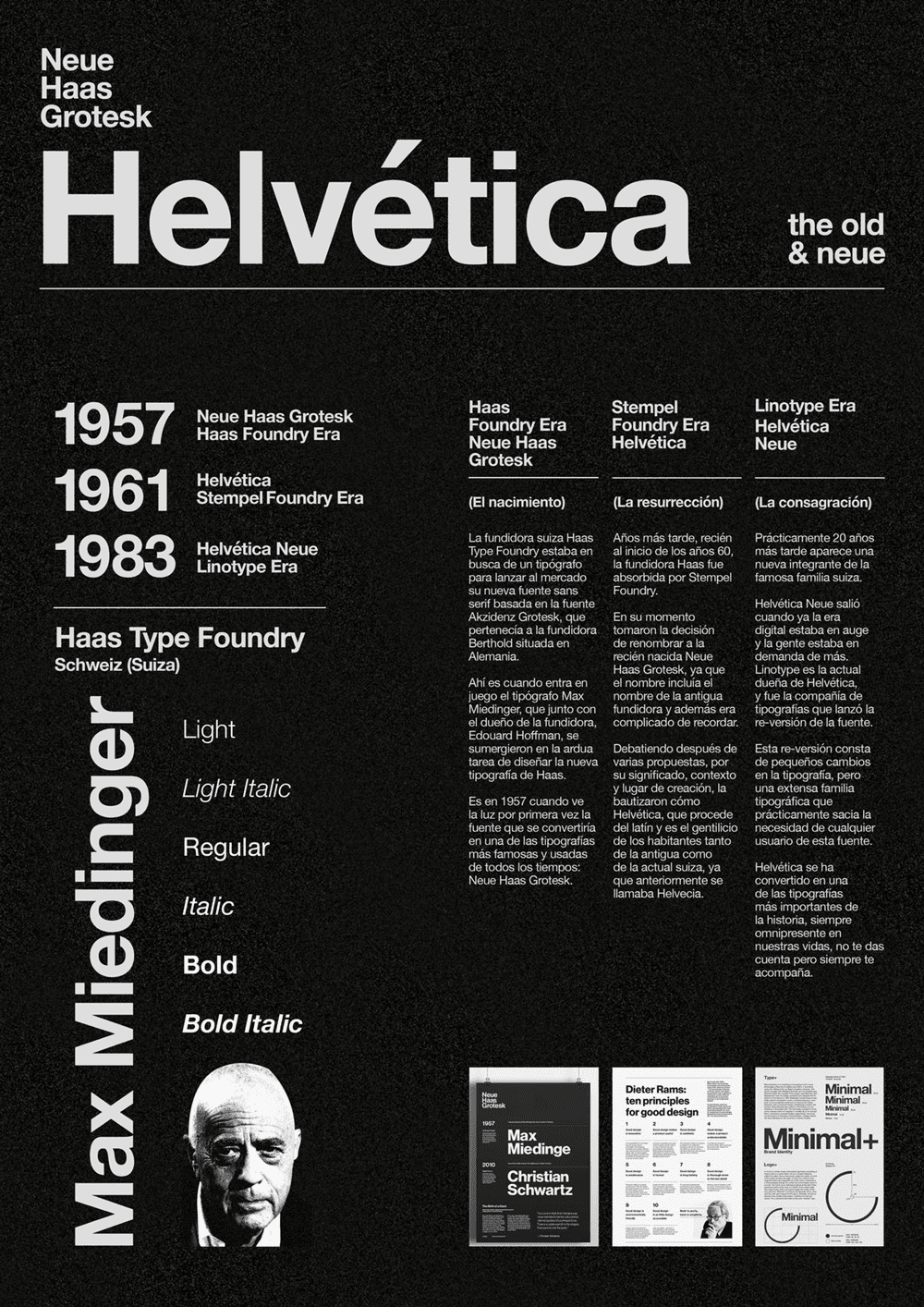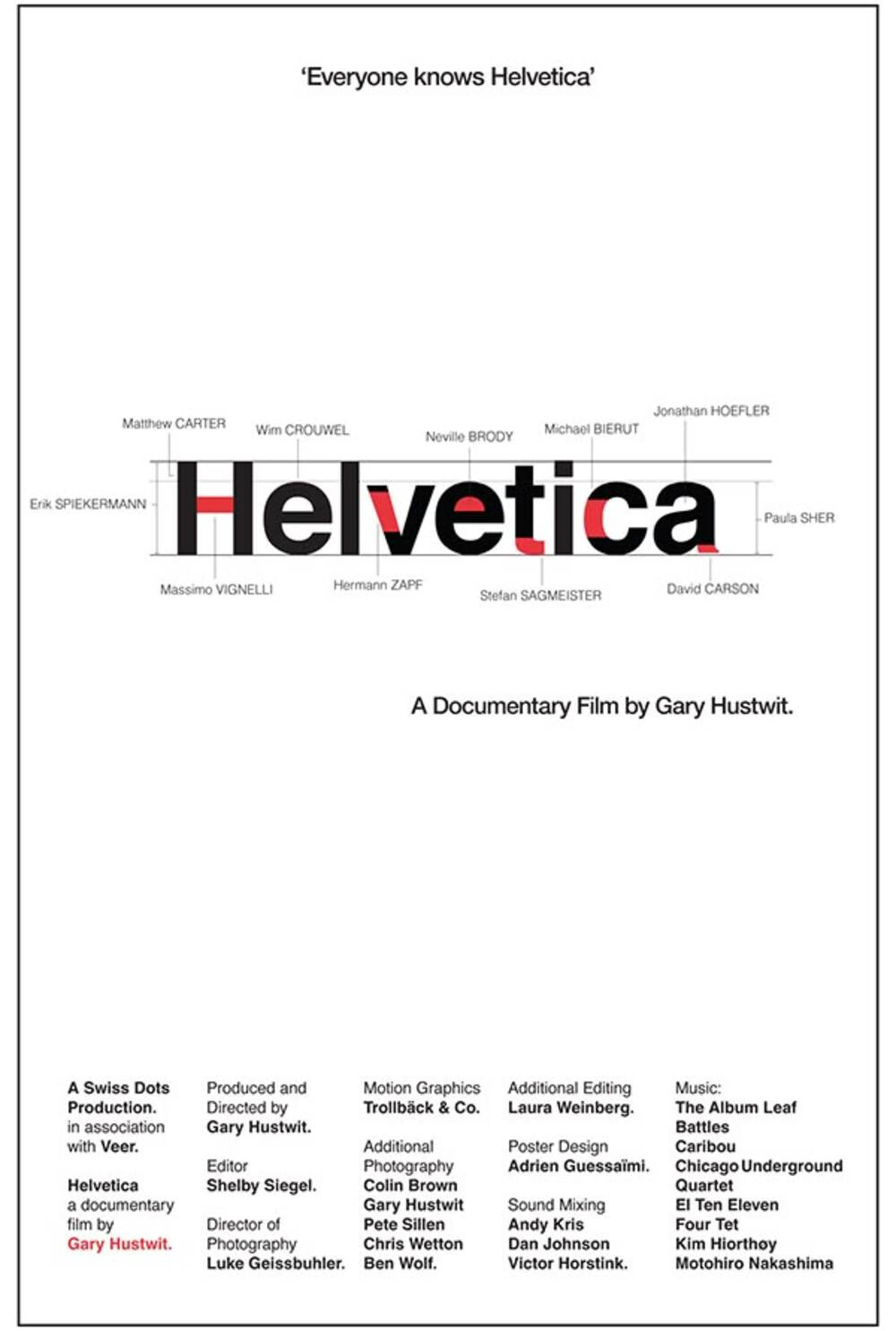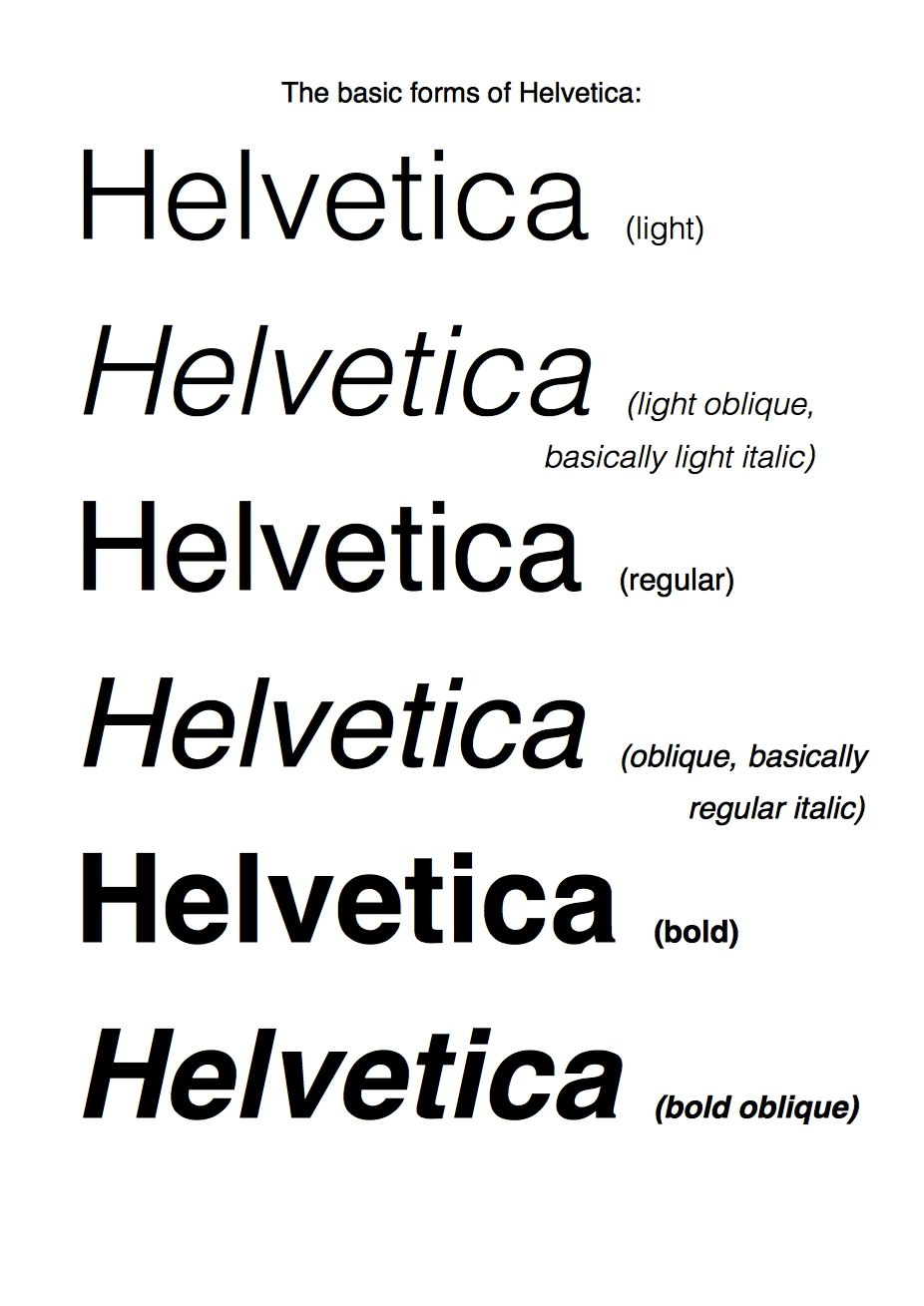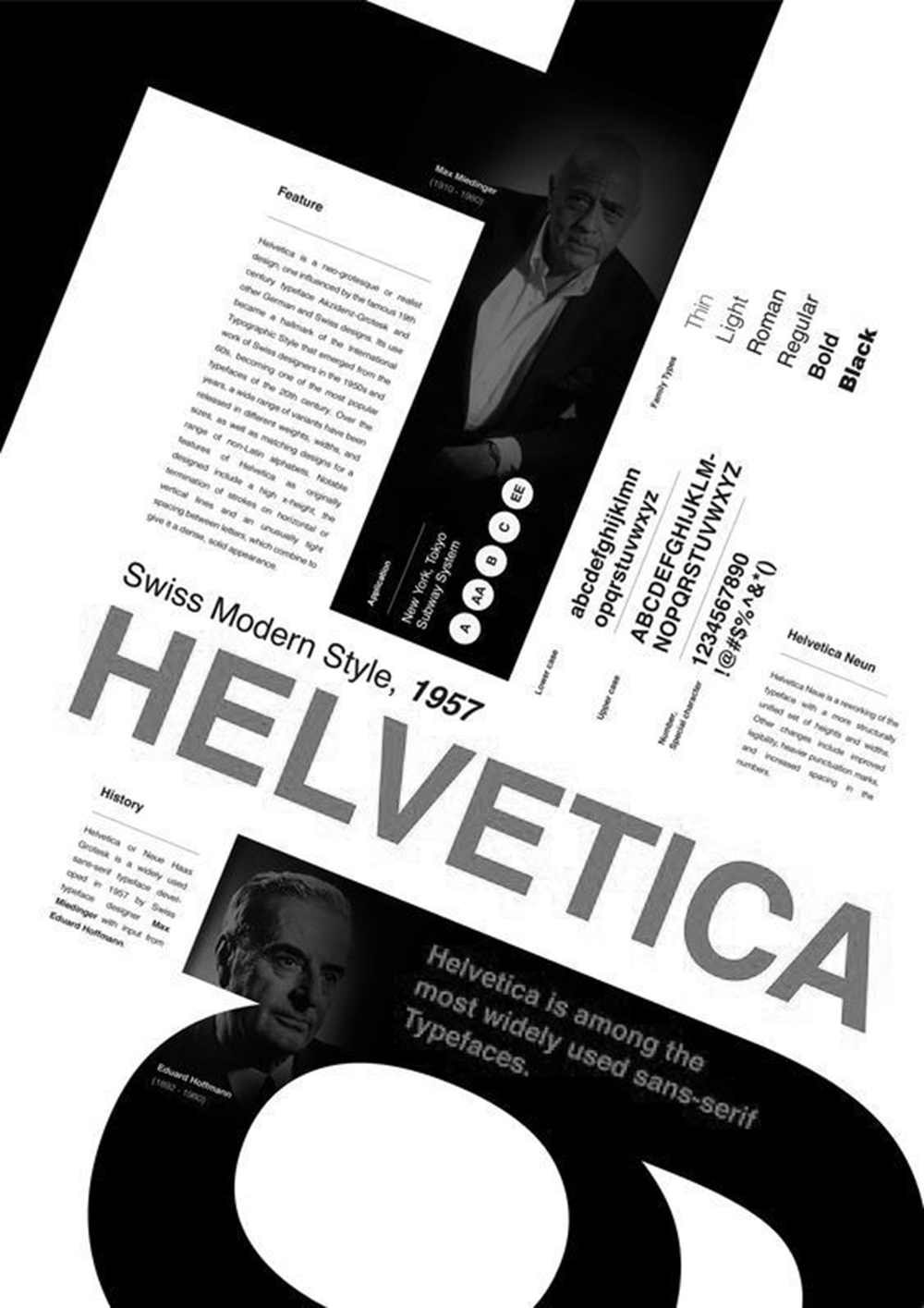
Helvetica Font là một trong những font chữ sans serif nổi tiếng và được sử dụng phổ biến nhất hiện nay trong thiết kế đồ họa, in ấn và branding. Với phong cách tối giản, hiện đại cùng khả năng hiển thị rõ ràng, Helvetica luôn được nhiều designer lựa chọn cho logo, poster, banner và các ấn phẩm truyền thông chuyên nghiệp.
Helvetica Font là gì?
Font Helvetica tổng hợp
Helvetica Font là một kiểu chữ sans serif nổi tiếng với phong cách tối giản, hiện đại và dễ đọc. Font được phát triển vào năm 1957 tại Thụy Sĩ bởi nhà thiết kế Max Miedinger và nhanh chóng trở thành một trong những kiểu chữ phổ biến nhất thế giới. Nhờ khả năng hiển thị rõ ràng ở nhiều kích thước khác nhau, Helvetica được ứng dụng rộng rãi trong thiết kế đồ họa, quảng cáo, in ấn và nhận diện thương hiệu. Đến nay, Helvetica vẫn được xem là một trong những font chữ kinh điển có tính ứng dụng cao trong ngành thiết kế.
Đặc điểm nổi bật của Helvetica Font
Helvetica là bộ font chữ được yêu thích nhờ khả năng hiển thị rõ ràng, dễ nhìn và phù hợp với nhiều phong cách thiết kế khác nhau. Bộ font này mang lại cảm giác chuyên nghiệp, hiện đại và thường được sử dụng trong các ấn phẩm quảng cáo, nhận diện thương hiệu và thiết kế in ấn.
Đặc điểm font Helvetica
Một số điểm nổi bật của Helvetica:
- Ký tự cân đối, khoảng cách chữ dễ nhìn
- Hiển thị tốt trên cả màn hình và bản in
- Có nhiều độ đậm khác nhau để dễ phối hợp thiết kế
- Phù hợp cho logo, poster, catalogue, bao bì
Bộ font đầy đủ các độ đậm
Bộ font Helvetica
Bộ Helvetica Font Việt hóa thường bao gồm nhiều kiểu chữ khác nhau như:
- Helvetica Light
- Helvetica Regular
- Helvetica Medium
- Helvetica Bold
- Helvetica Black
Việc sở hữu đầy đủ các độ đậm giúp designer dễ dàng xây dựng bố cục và phân cấp nội dung hiệu quả hơn.
Một số font tương tự Helvetica có thể tham khảo
Nếu yêu thích phong cách tối giản của Helvetica, bạn cũng có thể tham khảo thêm nhiều kiểu chữ tương tự dưới đây.
Các font tương tự Helvetica
Arial
Arial có thiết kế khá gần với Helvetica và được sử dụng phổ biến trong văn phòng, tài liệu và thiết kế cơ bản.
Univers
Univers là font chữ sans serif nổi tiếng với hệ thống độ đậm đa dạng, phù hợp cho thiết kế chuyên nghiệp và nhận diện thương hiệu.
Roboto
Roboto được Google phát triển với phong cách hiện đại, dễ đọc và tối ưu tốt cho giao diện kỹ thuật số.
Montserrat
Montserrat sở hữu thiết kế trẻ trung, hiện đại và thường được sử dụng trong thiết kế social media, website và banner quảng cáo.
SF Pro Display
SF Pro Display là font chữ do Apple phát triển với khả năng hiển thị đẹp mắt trên các thiết bị công nghệ và giao diện hiện đại.